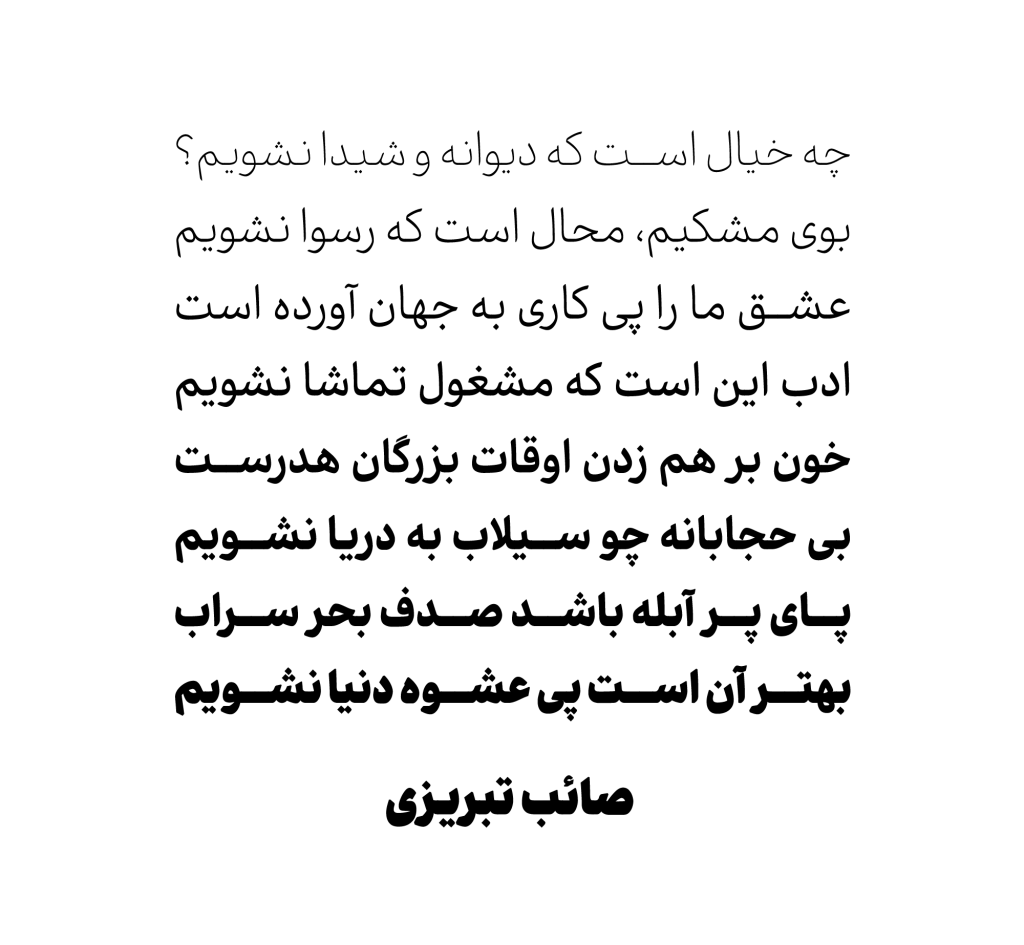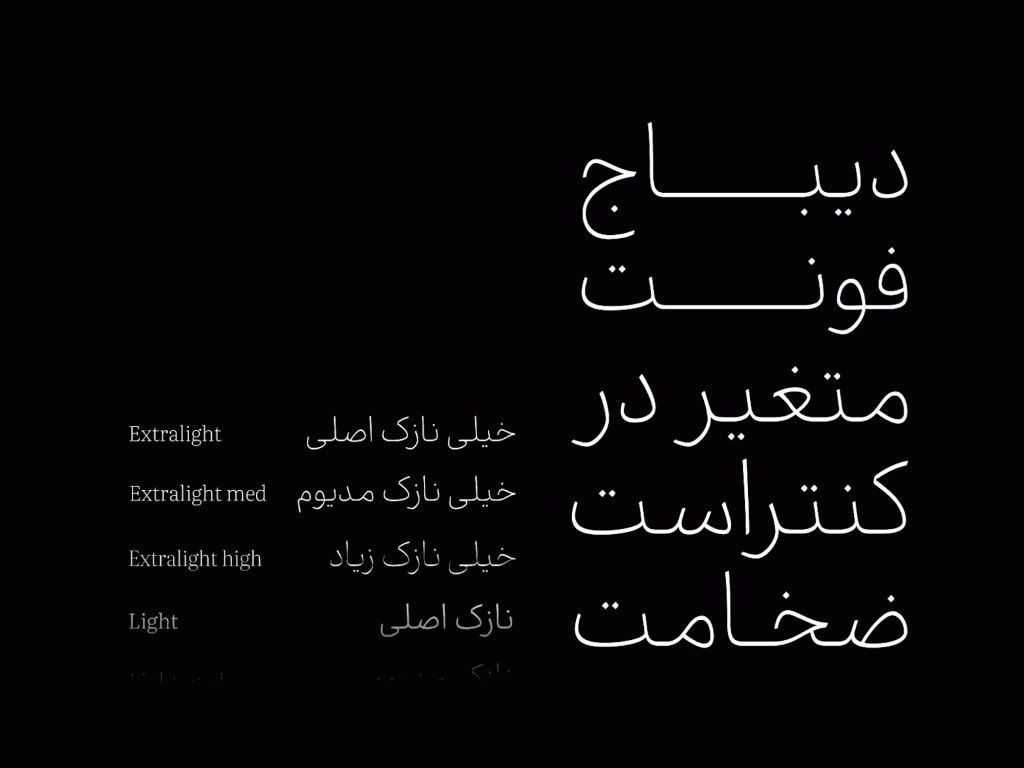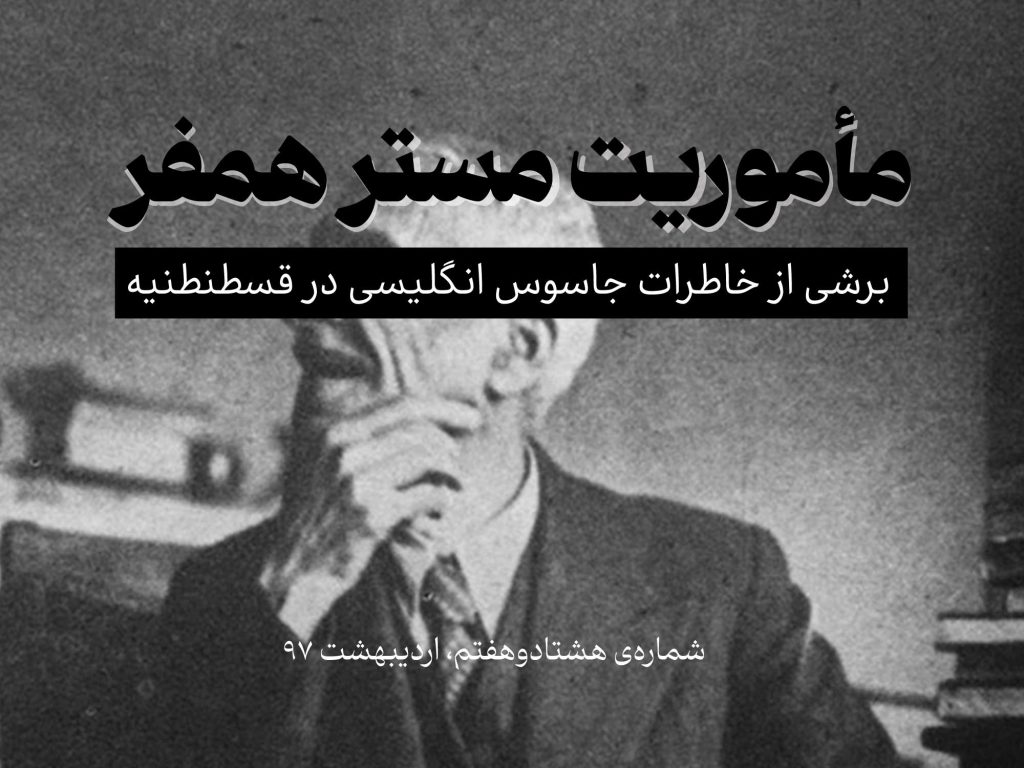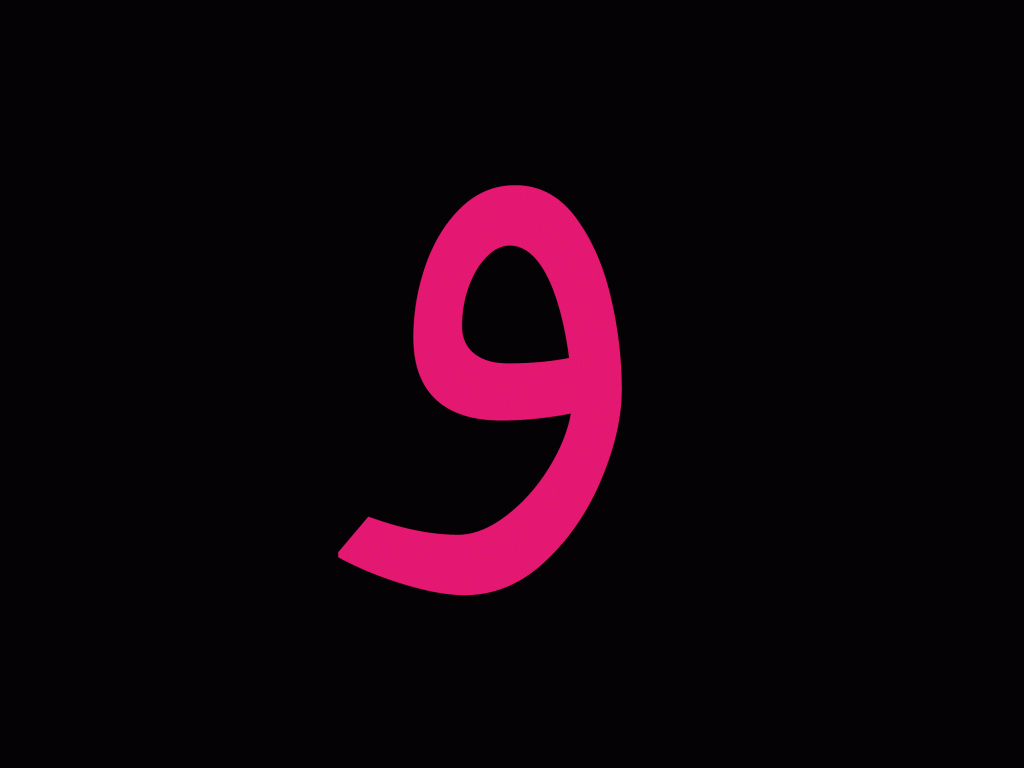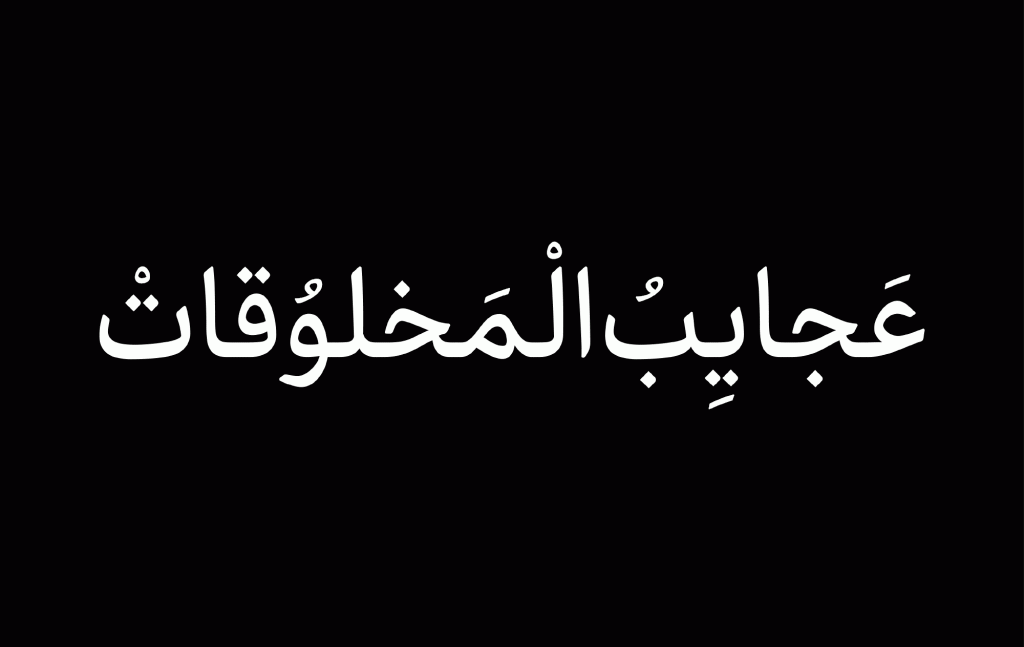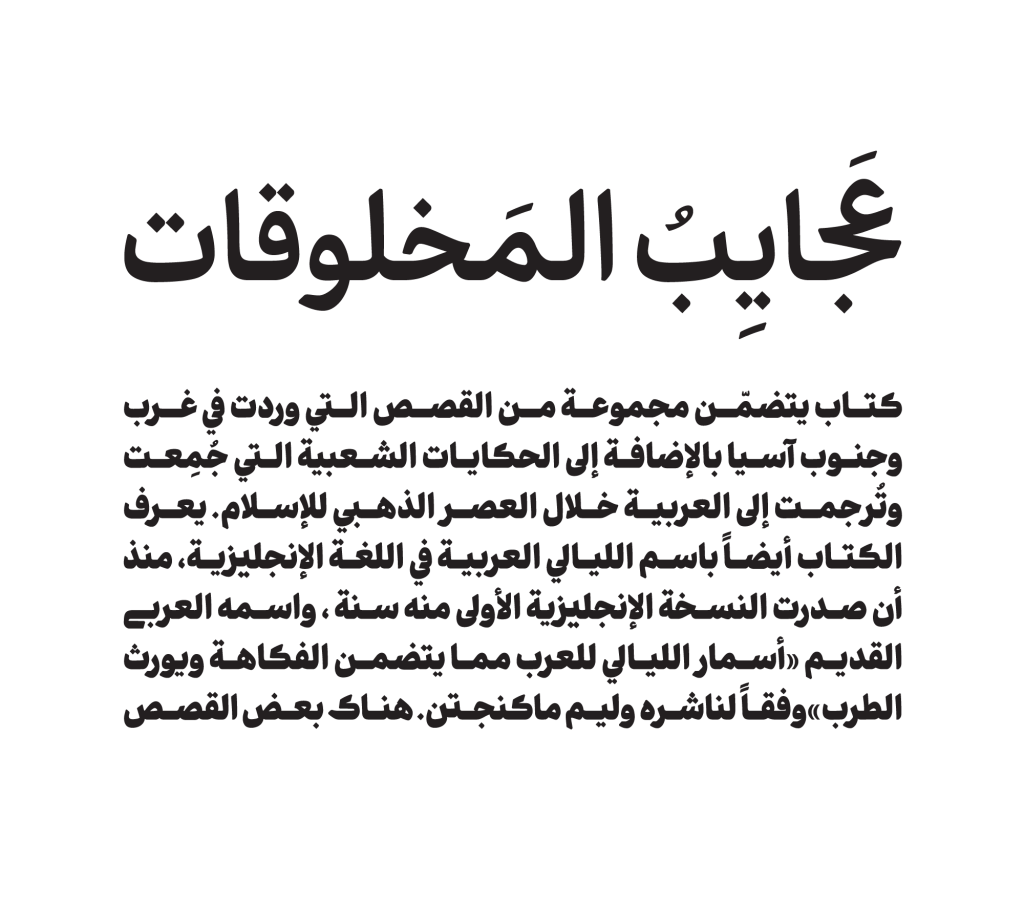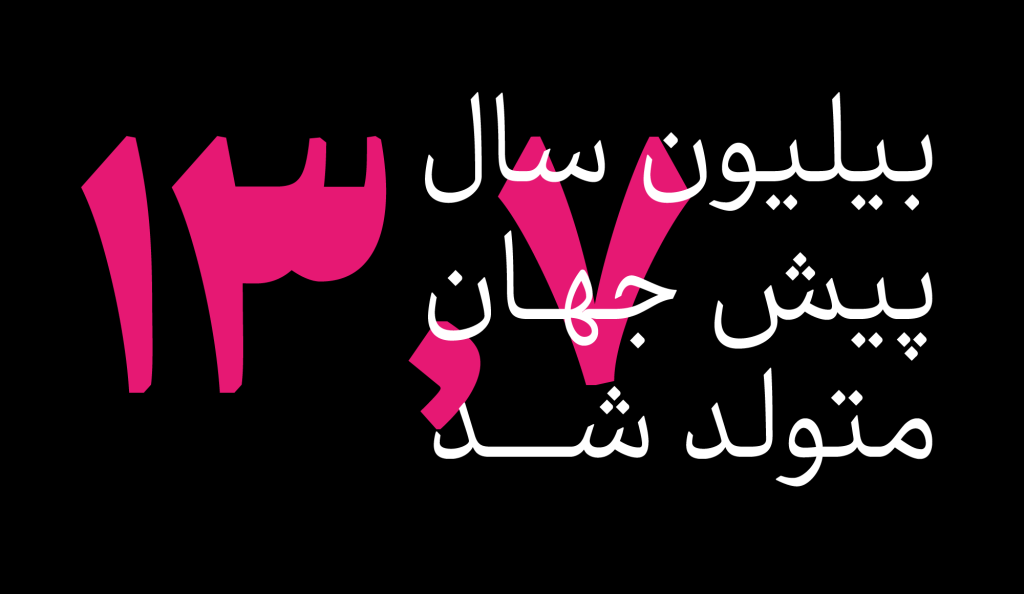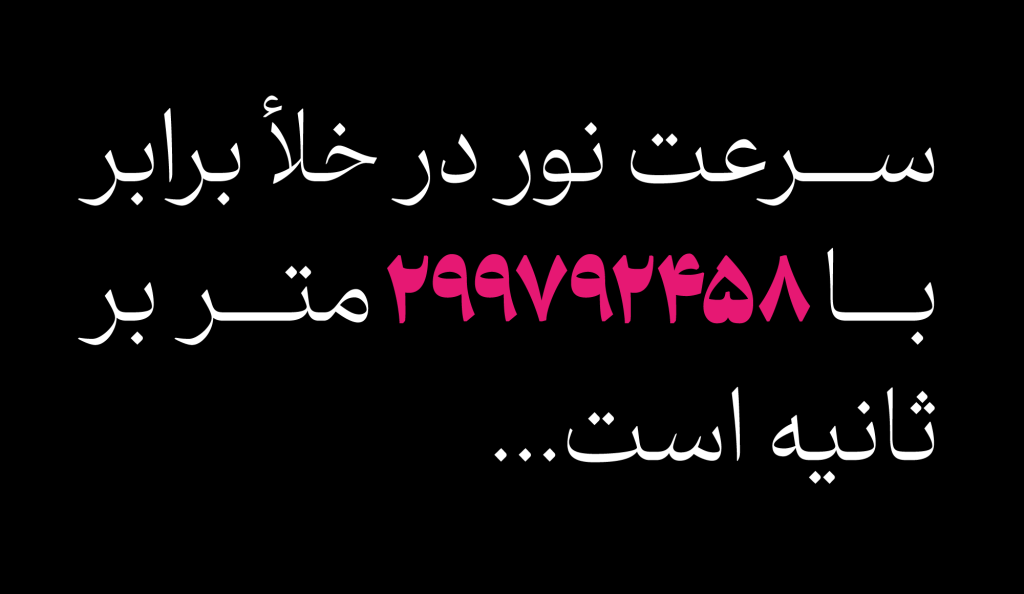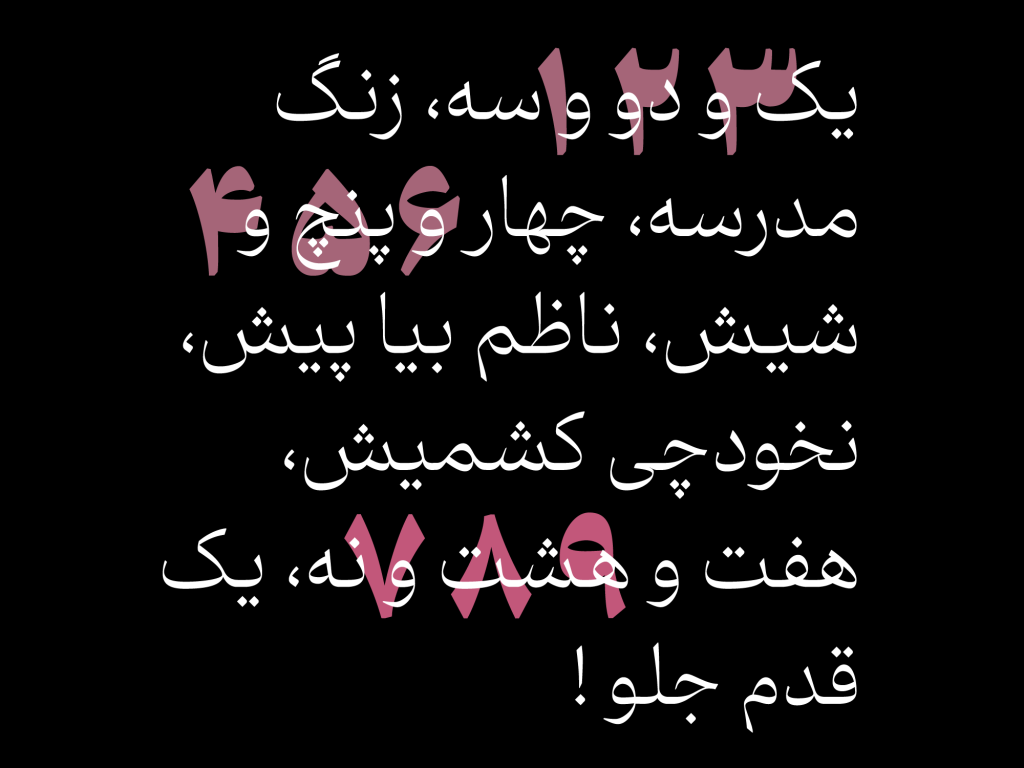
فونت دیباج
فونت دیباج قلمی چند منظوره با وزن و استایل های متفاوت، حروف و ترکیبات جایگزین ، دارای نسخه متغیر یا وریبل و…همه ی آنچه را که طراحان به دنبال هستند، در دل خود دارد.دیباج روایتگر است و با دارا بودن لحنی صمیمی وروان ، روایتگری برای داستان ها ، اتفاقات و رویدادهای جذاب است.
دیباج تایپ فیسی چند منظوره میباشد. به عبارتی دیگر این قلم در وزن های پایین و سبک مناسب متون طولانی و بلند است. و در اوزان سنگین به سبب دارا بودن ویژگی نمایشی بالا قابلیت استفاده در متون کوتاه و عناوین و تیتر های تبلیغاتی را دارد.دیباج اساسا برای متن طراحی شده است .یکی از اهداف طراحی دیباج رسیدن به قدرت شگرف در خوانایی برای متون ریز و طولانی(7_12pt) بوده است.
حلقه های نسبتا بزرگ ، خطوط کرسی منظم و محدود ، رعایت اصول فاصله گذاری درستِ متناسب با ریتم و آهنگ، از جمله دلایلی است که به خوانایی این قلم افزوده است .نسبت دور بیشتر در فرم منحنی حروف سبب حرکت راحت تر چشم ها بر روی سطرها گردیده از این رو دیباج را به قلمی روان و سیال مبدل ساخته است.
این تایپ فیس از خط محقق اقتباس گرفته است .یکی از چالش های اصلی در طراحی دیباج تلاش برای افزودن روحیه ی مدرن و امروزی در عین حفظ شاکله اصلی خط محقق بوده است.با کمی دقت در تصاویر نمونه این قلم ، کاملا مشخص است که در اوزان سنگین ، از دور حروف کاسته شده و فراز و فرودها کوتاه تر شده و کنتراست سطحی قلم تشکیل میشود و همین امر سبب افزایش ویژگی نمایشی و جذب نگاه خوانندگان برای عناوین و تیترهای نوشتاری میشود.
خانواده ی دیباج با داشتن ۹ وزن و ۳ سبک و استایل متفاوت تنوع گسترده ای از وزن های (extra light……extra black)برای خلق هر نوع طرح دست طراحان را باز گذاشته است .
دیباج با بهره مندی از تکنولوژی وریبل فونت ، تمامی وزن ها سبک های نوشتاری ، حروف جایگزین و… را در یک فایل با عنوان و وریبل یا متغیر به شما ارائه میدهد.حجم کمتر و سرعت بیشتر خصوصا در صفحات وب و شبکه مجازی از مزایای این تکنولوژی محسوب می شود.
پشتیبانی از ترکیبات جایگزین در دیباج
این قلم همانطور که گفته شد همه ی آنچه طراحان نیاز دارند، در دل خود جای داده است .پشتیبانی از حروف وترکیبات جایگزین سبب خلق تنوع و زیبایی بیشتر در متون و نوشته ها میگردد . در فایل راهنمای این محصول نحوه فعالسازی این ترکیبات به شما عزیزان ارائه شده است.
این تایپ فیس از زبان فارسی، عربی و انگلیسی پشتیبانی میکند.